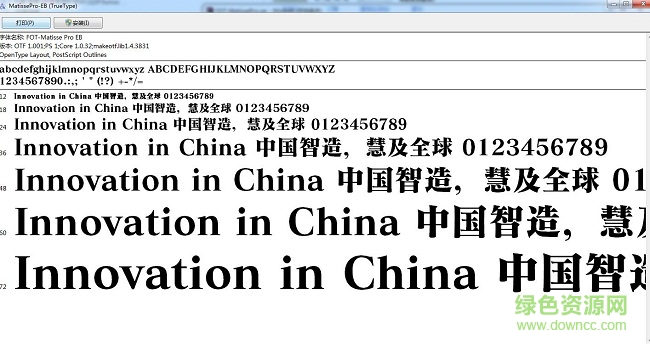
matisse eb字體又叫eva明朝體,是一款設(shè)計(jì)精細(xì)的優(yōu)美日文字體,筆畫(huà)簡(jiǎn)約,線條柔和,常常用于二次元?jiǎng)勇?a href="http://www.italianbookmakers.com/k/haibaosheji/" target="_blank">海報(bào)設(shè)計(jì),制作效果非常好,感興趣的朋友可以下載試試!
出自日本字體設(shè)計(jì)公司Fontworks之手。在DTP(桌面出版系統(tǒng))剛剛起步的90年代初期,公司創(chuàng)始成員之一的佐藤俊泰利用一臺(tái)mac電腦,對(duì)傳統(tǒng)明朝體進(jìn)行了精細(xì)的改良,終于在 94年發(fā)布了這款全新感覺(jué)的字體,該字體不僅有著強(qiáng)烈的視覺(jué)沖擊力,字體本身就帶有感情,能夠表達(dá)出很多東西!